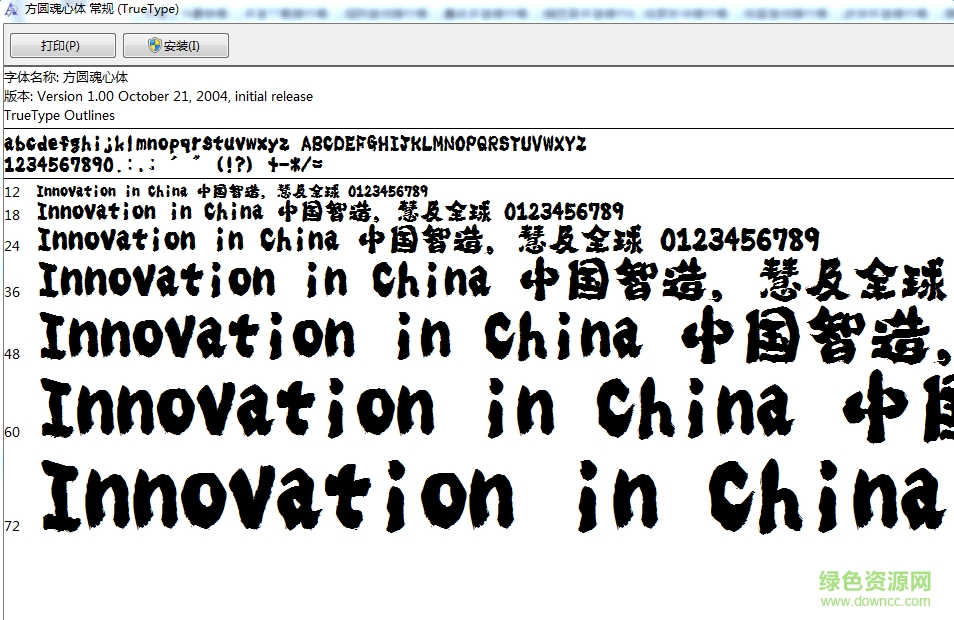
方圓魂心體常規(guī)字體
方圓魂心體是一款時(shí)尚胖體風(fēng)格字體軟件,方圓魂心體筆畫看似潦草粗狂,卻給人非常醒目的感覺,十分搞怪,在海報(bào)廣告標(biāo)題設(shè)計(jì)方面有較深的應(yīng)用,還有更多好看字體歡迎到綠色資源網(wǎng)下載使用!
方圓魂心體